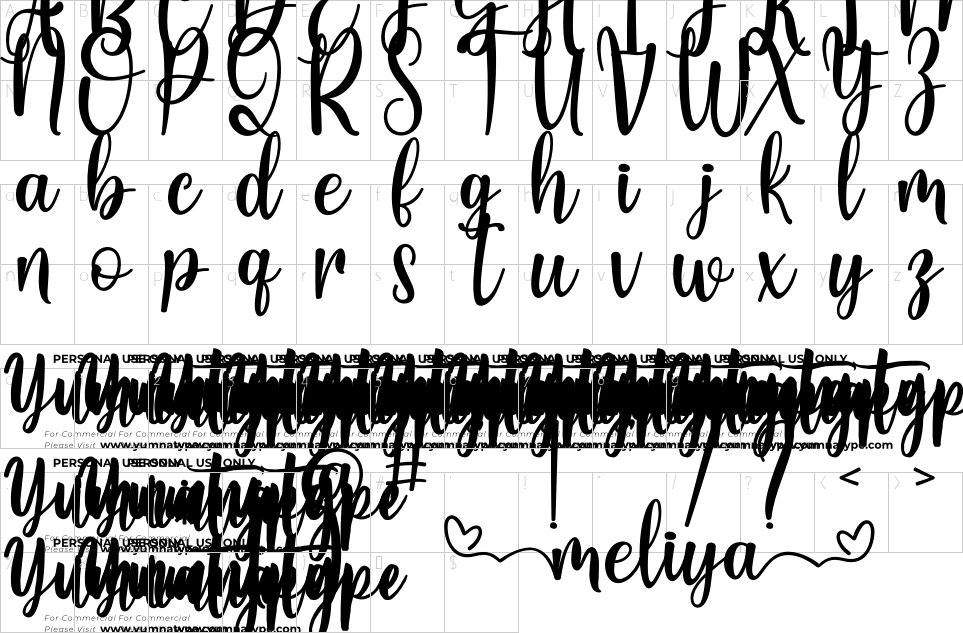
A Meliya font é uma opção de destaque para designers e criadores de conteúdo no seu portfólio, oferecendo uma tipografia agradável e moderna. Desenvolvida pela Yumna Type, esta fonte é um recurso gratuito e poderoso para os amantes da boa gráfica. Com seu design cuidadosamente elaborado, a Meliya traz uma variedade de opções que vão desde linhas leves e elegantes até formas mais contornadas e interessantes. O fato de ser uma fonte gratuita para Windows e Mac, permite que designers com todos os orçamentos possam adicionar aprimoramentos gráficos a seus projetos. Desde seu download inicial, a fonte já foi descarregada mais de dois mil vezes, demonstrando sua popularidade e qualidade. Seja para usar em textos, headlines ou até mesmo em ícones de design de interface do usuário, a Meliya é uma escolha inteligente para qualquer projeto gráfico.